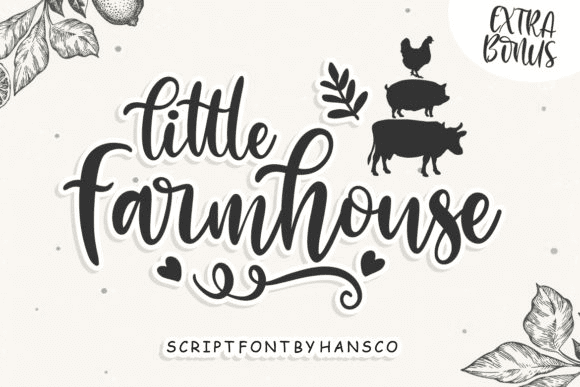
Название: Little Farmhouse Font
Маленькая ферма - это сладкий и нежный рукописный шрифт. Изысканный и радостный, этот шрифт будет идеально подходит для написания свадебных приглашений, открыток или любого другого дизайна, который может понадобиться романтичный, персонализированный штрих! Этот шрифт PUA закодирован, что означает, что вы можете получить доступ ко всем глифам и следам с легкостью!